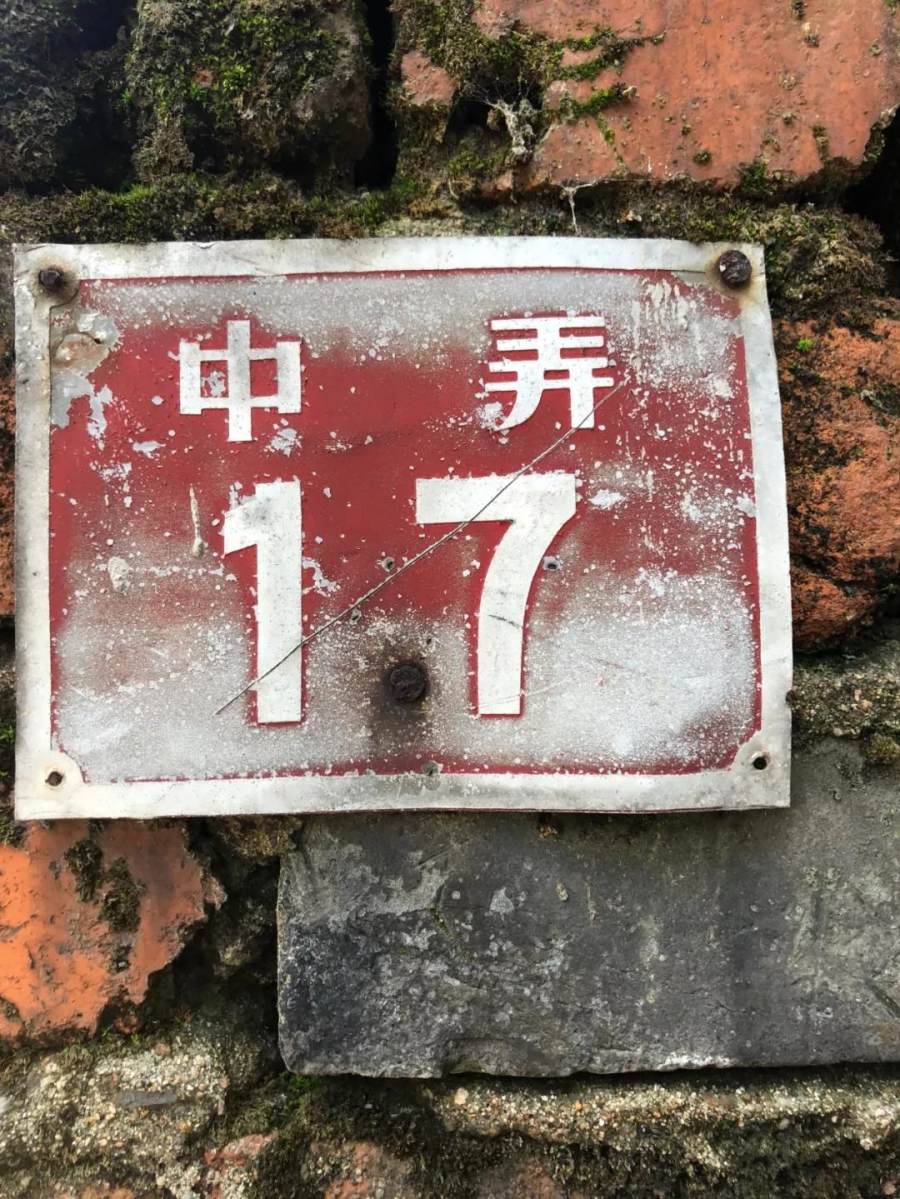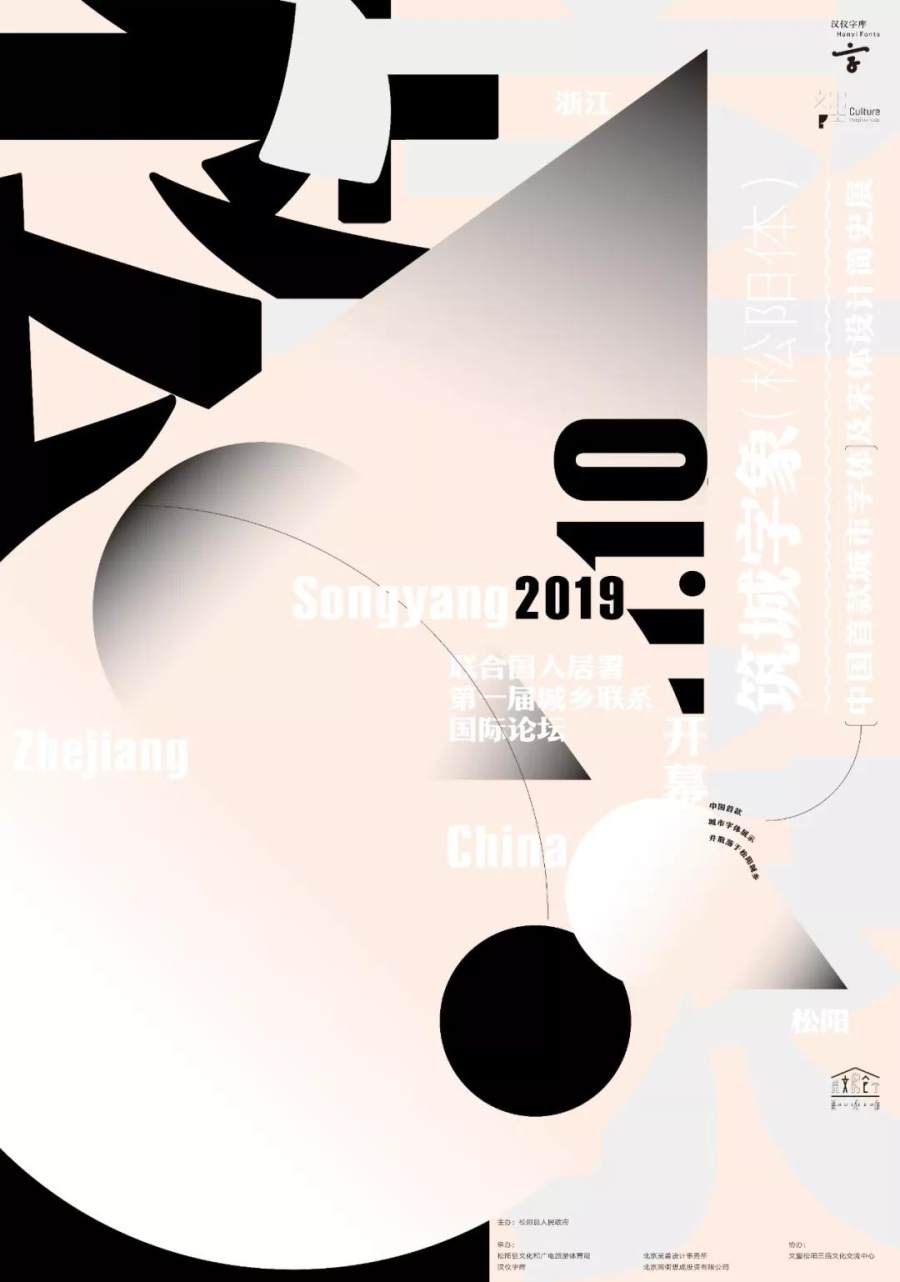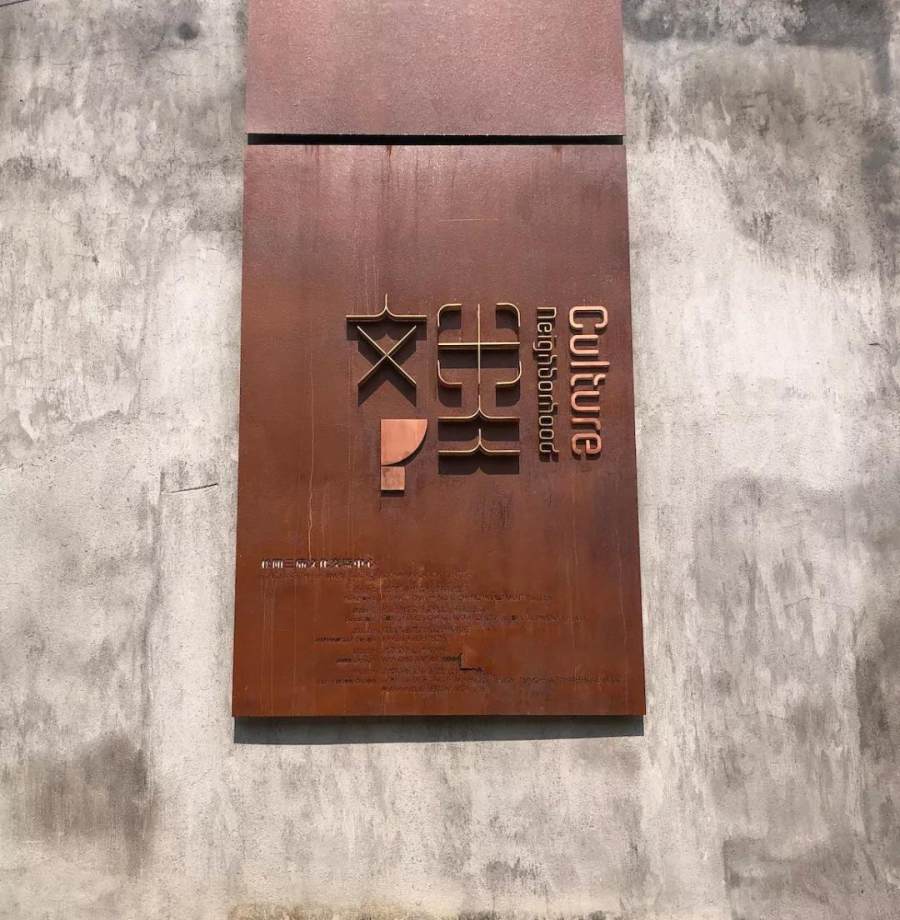
字如其人,字如其城。
在我们心中,每一座城市,都应该有只属于他的烟火与温度,以及与众不同的个性。
文字是文化的基因,城市文字也在以他自己的方式,
记录着你所看不到的城市故事,传承着千百年不息的人文精神。
松阳正是这样一座城。使用了几十年,至今在大部分老城区仍保存完好的门牌,
标记着每个松阳人心灵深处的家的记忆。
我们在采集的资料中找到的“中弄17”号
我们通过对松阳门牌字体的整理和再设计,得到了“汉仪松阳体“。
它以中国人最有情感的文字为桥梁,
为更多人开辟了一条从文字入手来解读一座城的路径。汉仪松阳体将带领你,走进不一样的松阳历史,
看到不一样的松阳生活,解读藏在文字里的这个“江南最后的秘境”。
汉仪松阳体由著名设计师吴勇&汉仪字库高级字体设计师刘宇共同设计,
经汉仪字库艺术顾问、著名字体设计师朱志伟指导,在松阳县政府的支持下完成,
作为联合国人居署第一届城乡联系国际论坛的子活动,
中国首款城市字体 —— 汉仪松阳体,将于2019年11月10日,在国际论坛举办期间,
通过“筑城字象“主题展览在浙江松阳正式发布。
作为松阳城市文化建设的探索性项目,包括松阳县政府在内的参与各方在展览开幕式上,
将就如何深度挖掘松阳城市的文化基因,
通过汉字人们激发对传统文化的情感,
打造一条用汉字创意开发带动本地文旅产业发展的独特路径进行主题分享与交流。
筑城字象 —— 中国首款城市字体及宋体设计简史展
汉仪松阳体在设计过程中,对松阳的历史文脉进行了系统梳理,
尤其是关注到松阳体与中国近代字体历史发展的关系。为了更好的呈现出城市、字体与人文生活之间的关系,
展览策划人吴勇老师特邀著名字体设计师岳昕老师携其风格独树一帜的字体作品,以“日常字像“主题展同期亮相。
“筑城字像”将和“日常字像”一起,像硬币的A、B面一样,既将松阳的不息文脉,
以松阳体的方式更加凝练系统的呈现出来,又以丰富多彩的汉字形态,
为包括联合国嘉宾在内的大量没有文字设计背景的观展人,呈现出丰富、完整的汉字表情,建立起汉字与城市、与人们生活的融洽关系。
日常字象 —— 岳昕先生字体设计展
松阳又被称为“古典中国”的县域样板,留存了非常丰富的历史文化资源。
松阳人一直在探索一条如何在最大程度保留历史文化资源的同时,又能让它们活起来,和松阳人们的生活和谐共生的路径。
值得一提的是,除了汉仪松阳字体,
本次发布仪式和展览的举办地——文里松阳三庙文化交流中心,同样也是对这种松阳精神的体现和充分诠释。
汉仪松阳体也已经成为文里三庙文化交流中心的导视字体。
字体和建筑,在对历史的尊重和对文化的创新的精神照耀下,相得益彰,熠熠生辉。